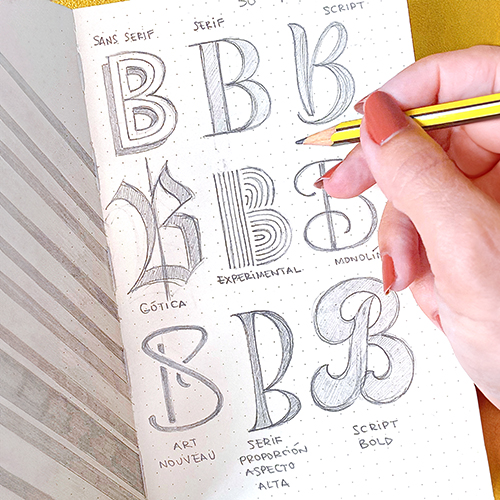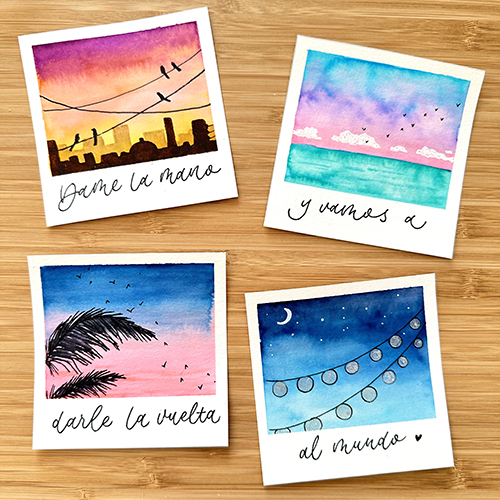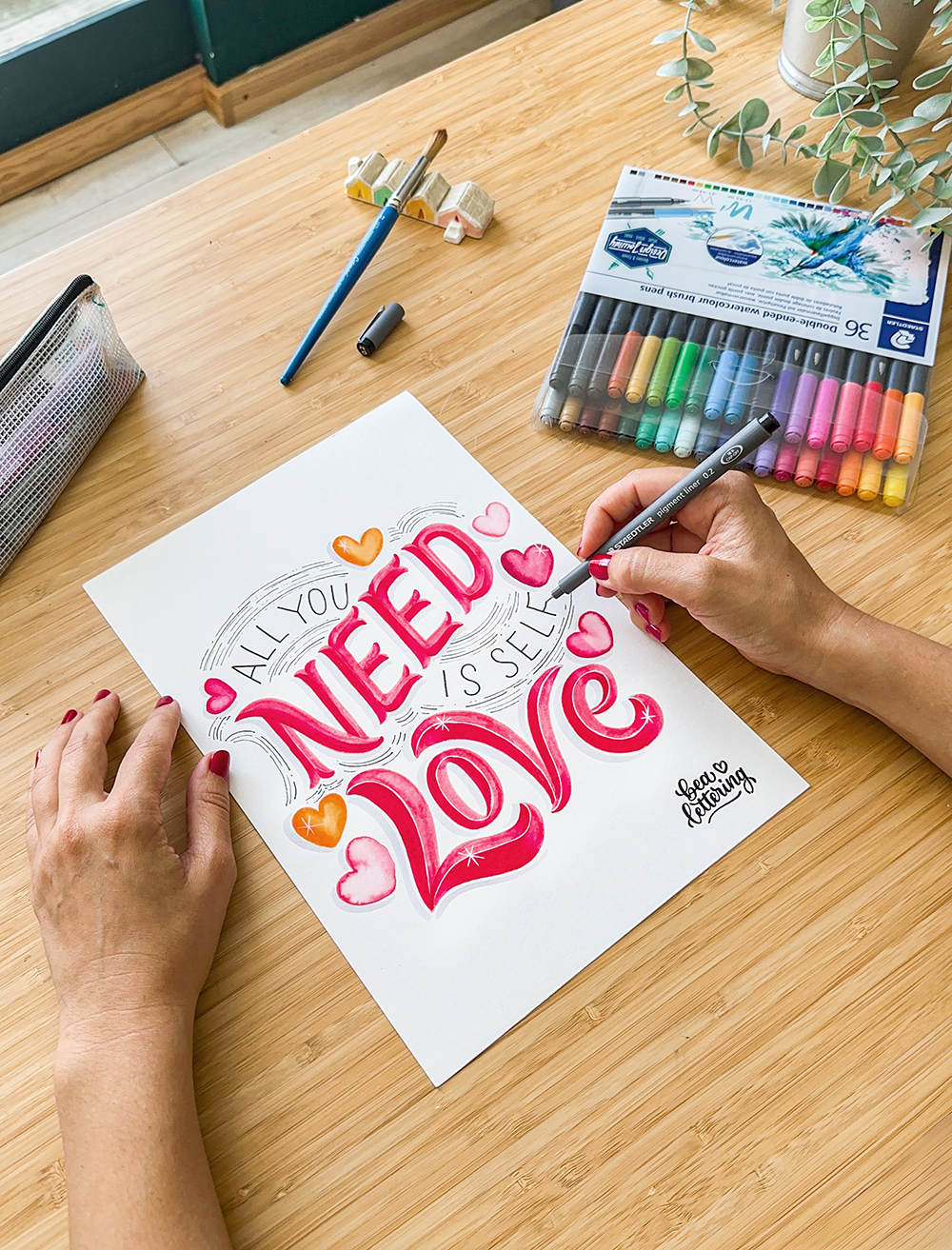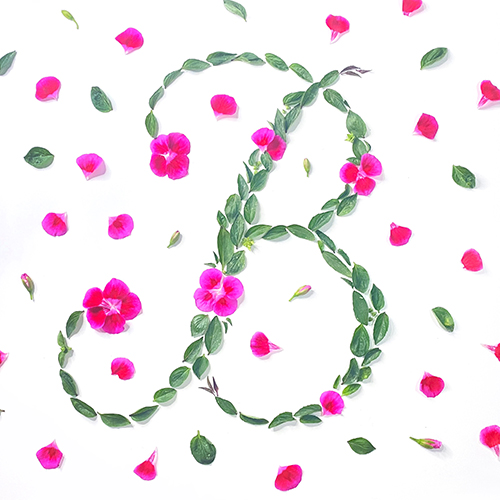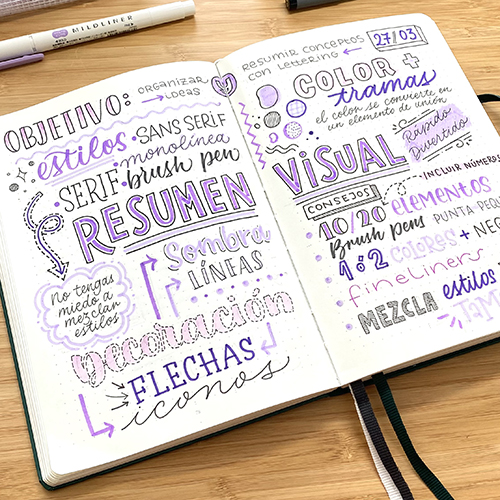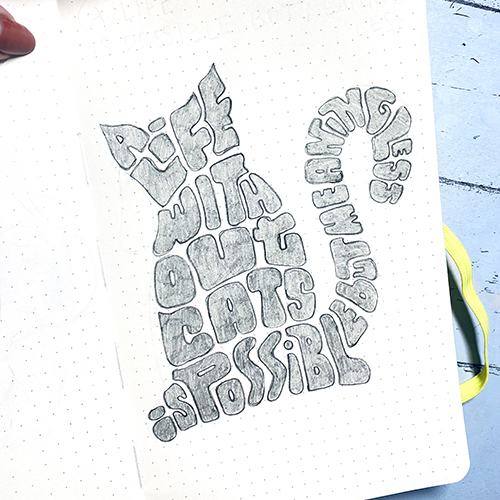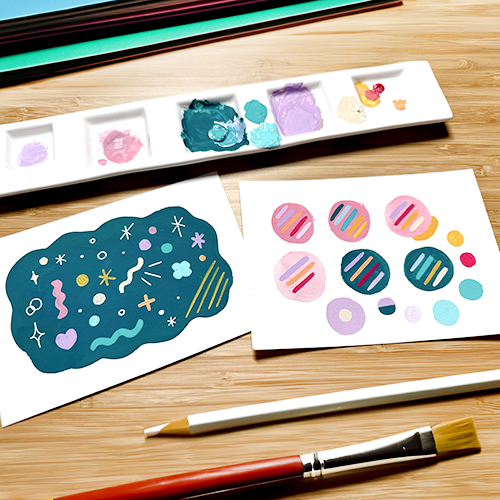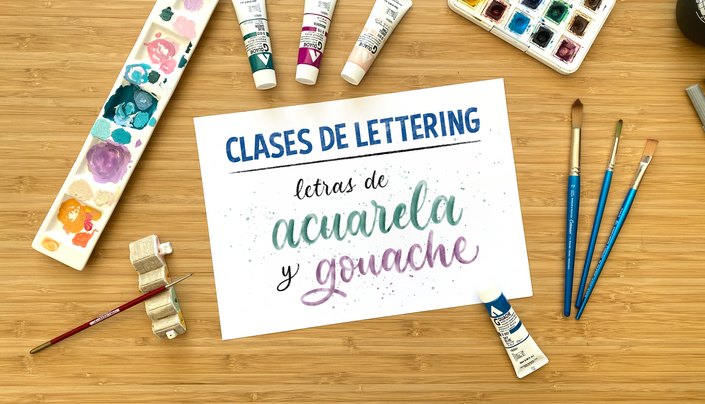
Qué encontrarás en este curso
Las clases incluyen pinceles específicos para cada proyecto que no se venden por separado, y que podrás utilizar en tus próximas creaciones.
Aquí tienes los proyectos que aprenderás a hacer
en estas clases:
Experimenta con materiales poco convencionales
En estas clases no nos limitamos a los brush pens, sino que exploramos diferentes materiales para crear piezas de lettering, desde lápices, acuarelas y gouache hasta sellos estampados o elementos de la naturaleza.
Aprende a crear multitud de estilos con rotuladores de punta redonda
Un solo rotulador puede llevarte muy lejos. En estas clases crearemos un repertorio de letras sencillas, llamativas y perfectas para utilizar en resúmenes visuales. ¡Prepárate para crear la portada de tu próximo viaje!
Con un montón de ejercicios creativos
Encontrarás clases de proyectos cortos en los que podrás explorar tu creatividad de una manera divertida, a la vez que preparas un cuaderno lleno de inspiración para futuros trabajos.
Define tu propio estilo
Empieza a definir tu estilo personal con una propuesta de actividades para encontrar qué es lo que te define, qué te gustaría incorporar a tus piezas y cómo hacer que tu trabajo sea fácilmente reconocible.
Prueba algo nuevo
Ya sea un nuevo material, una nueva paleta de color o una nueva forma de practicar composiciones, ¡seguro que en estas clases encuentras algo que no habías probado nunca!
Con proyectos para poner en práctica lo aprendido
Y, como siempre, con diferentees proyectos para aplicar todo lo que has aprendido y muchas ideas para presentar tu trabajo y compartirlo con todo el mundo.
Por qué aprender lettering es una buena idea
El lettering es una habilidad artística que no solo despierta tu creatividad, sino que también puede convertirse en una valiosa herramienta profesional.
Tanto si lo practicas como hobby o quieres explorar nuevas oportunidades laborales, aprender lettering te abre las puertas a un sinfín de posibilidades. Puedes aplicarlo en diseño gráfico, creación de logotipos, papelería personalizada, murales, y mucho más. Además, lo genial del lettering es que no estás limitado a un solo tipo de material: puedes experimentar con rotuladores, pinceles, acuarelas, tinta, e incluso herramientas digitales.